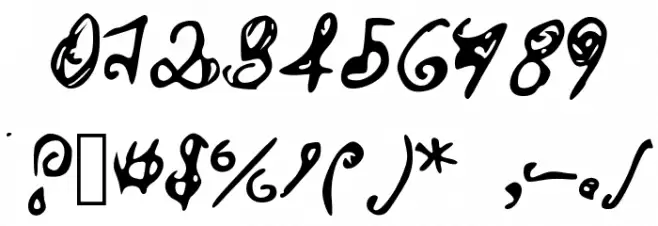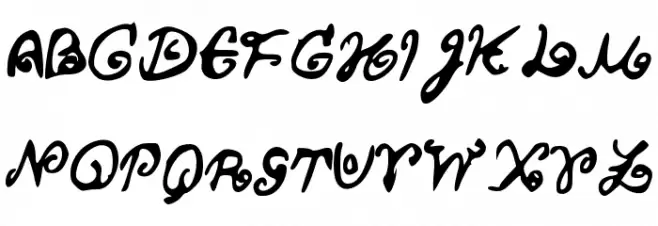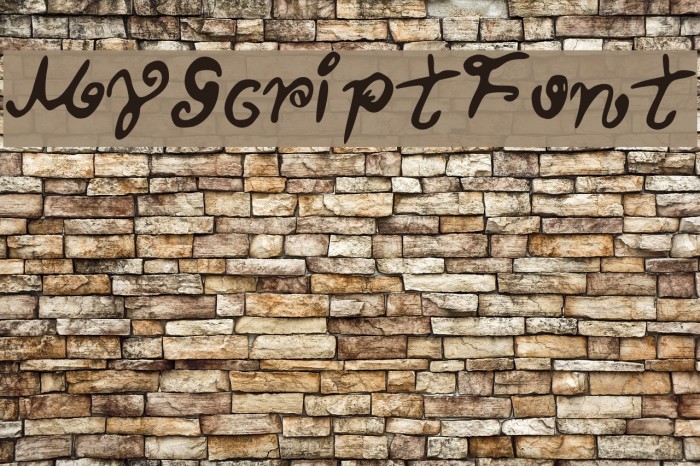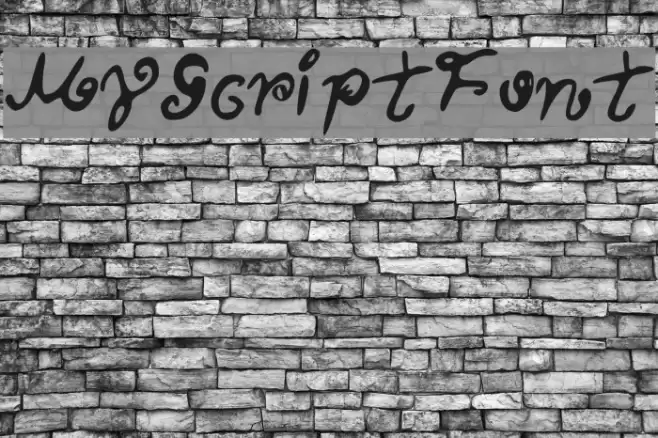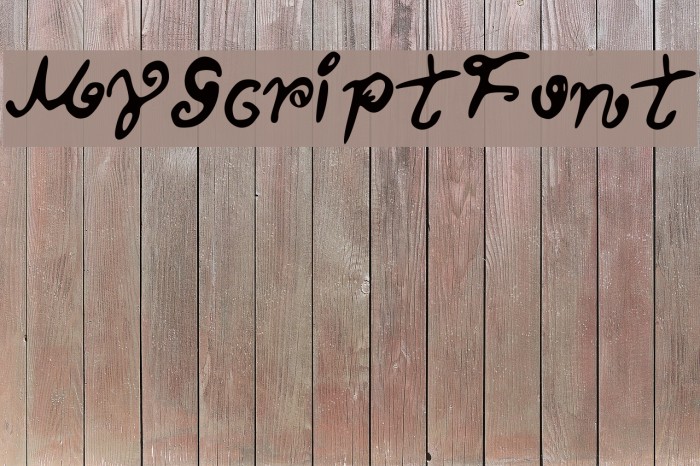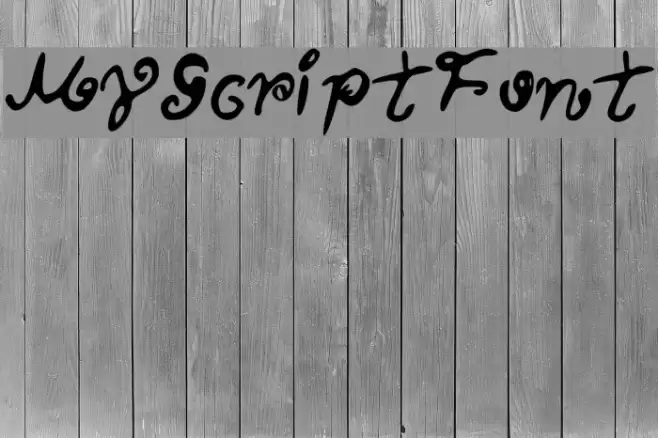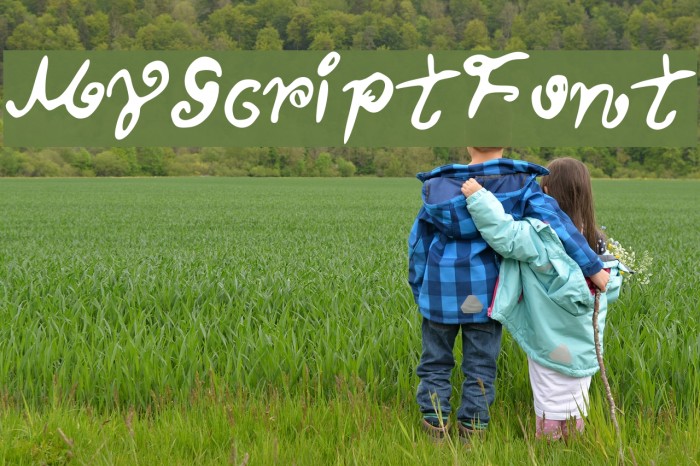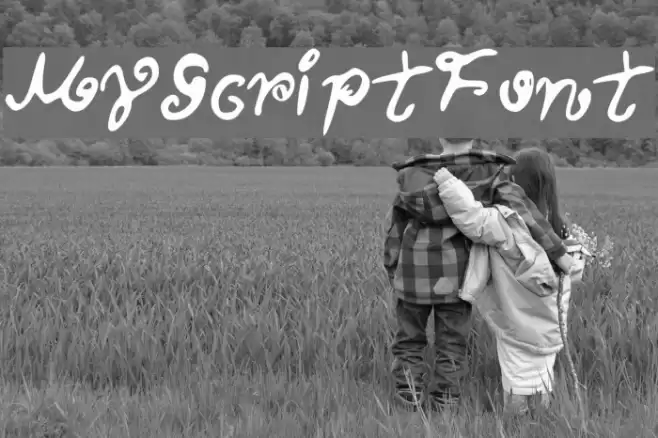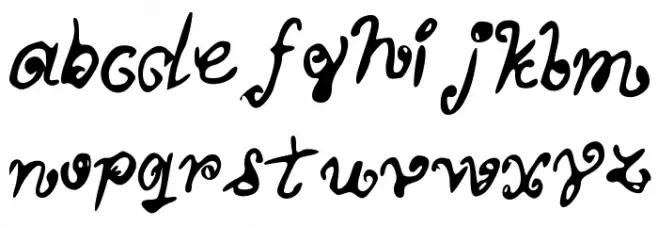
MyScriptFont Font
| Cas d'utilisation | Logos, Headlines, Creative projects |
| Projets proposés | Ideal for greeting cards, invitations, personal branding, and creative posters. |